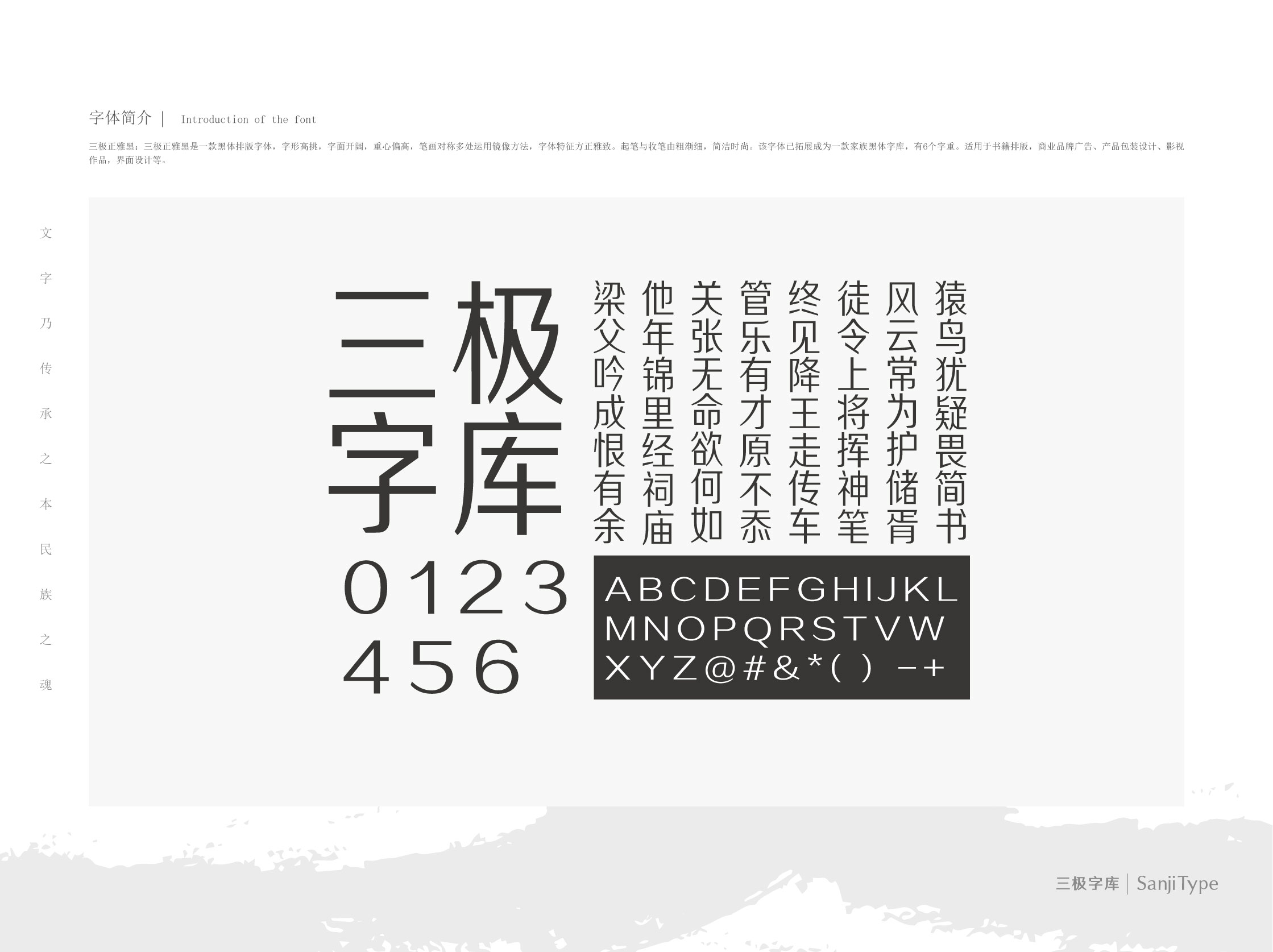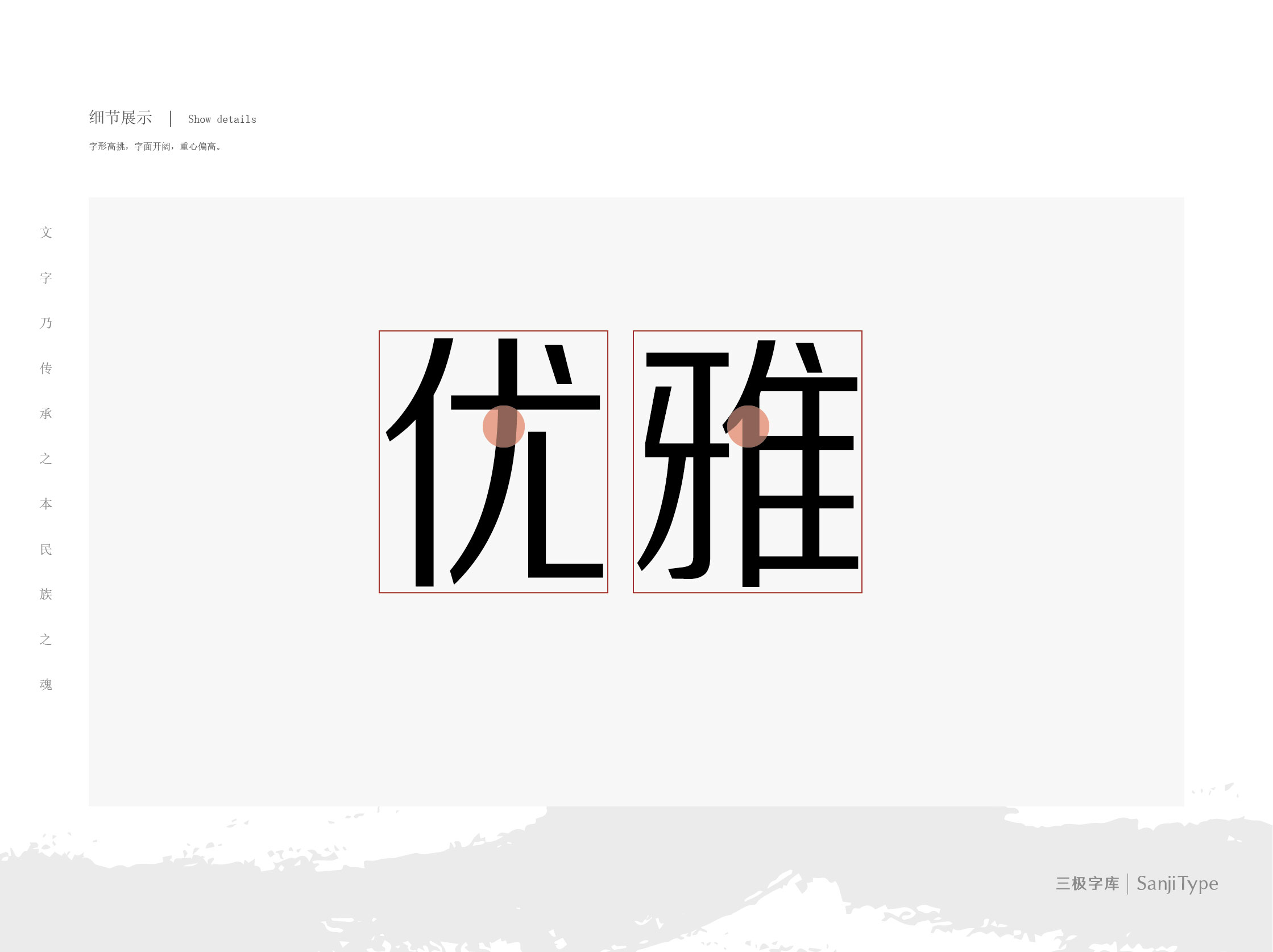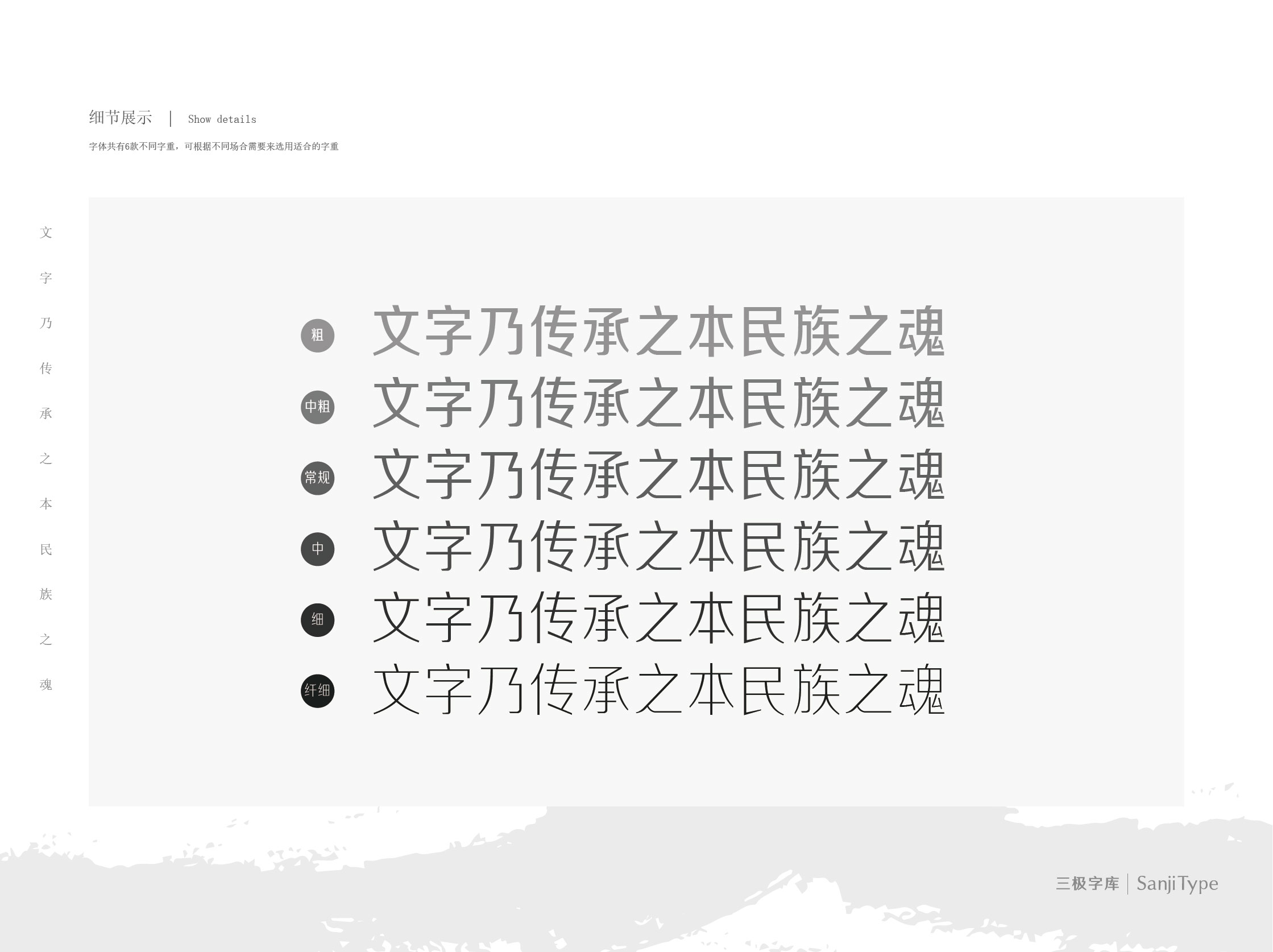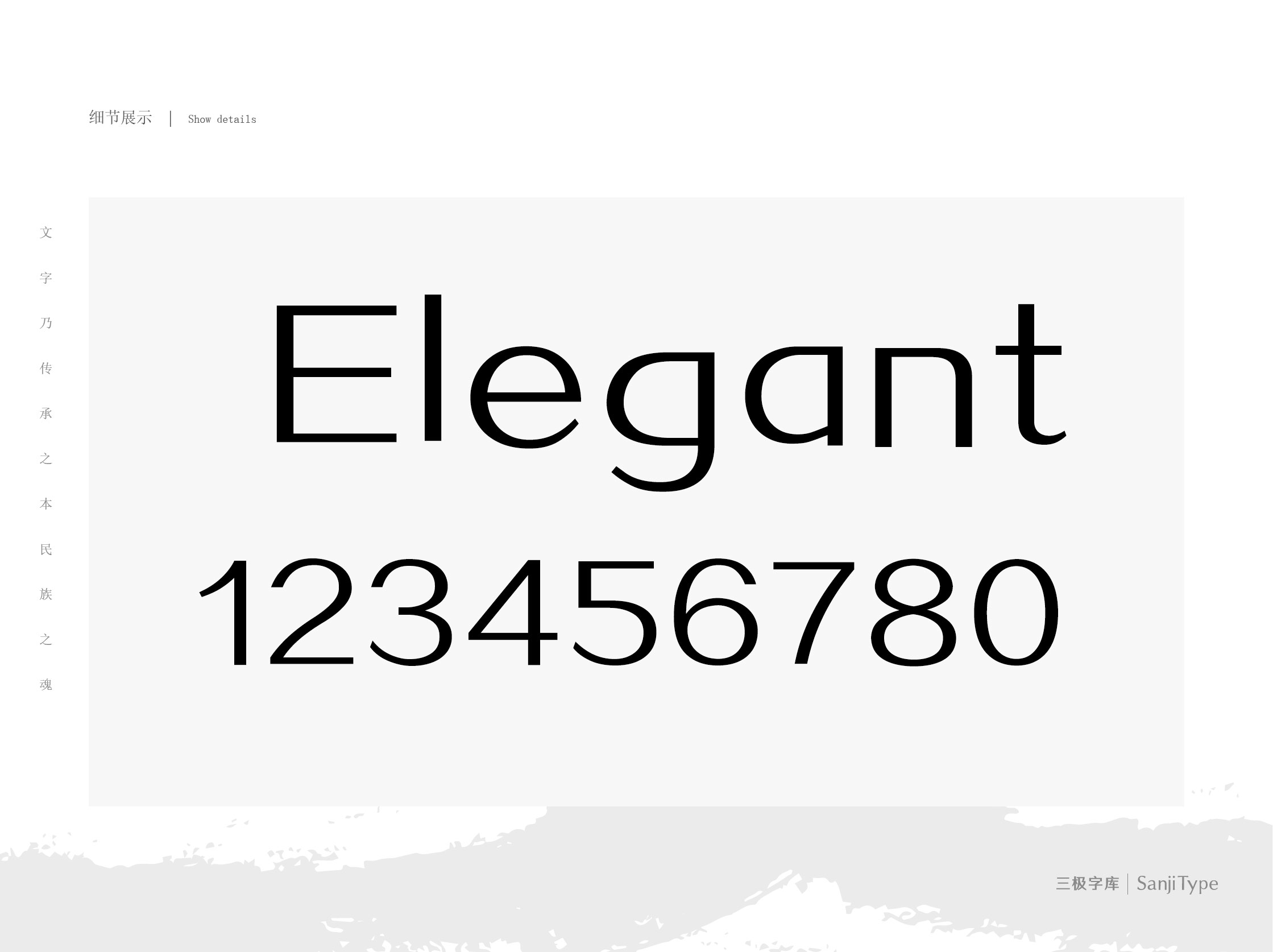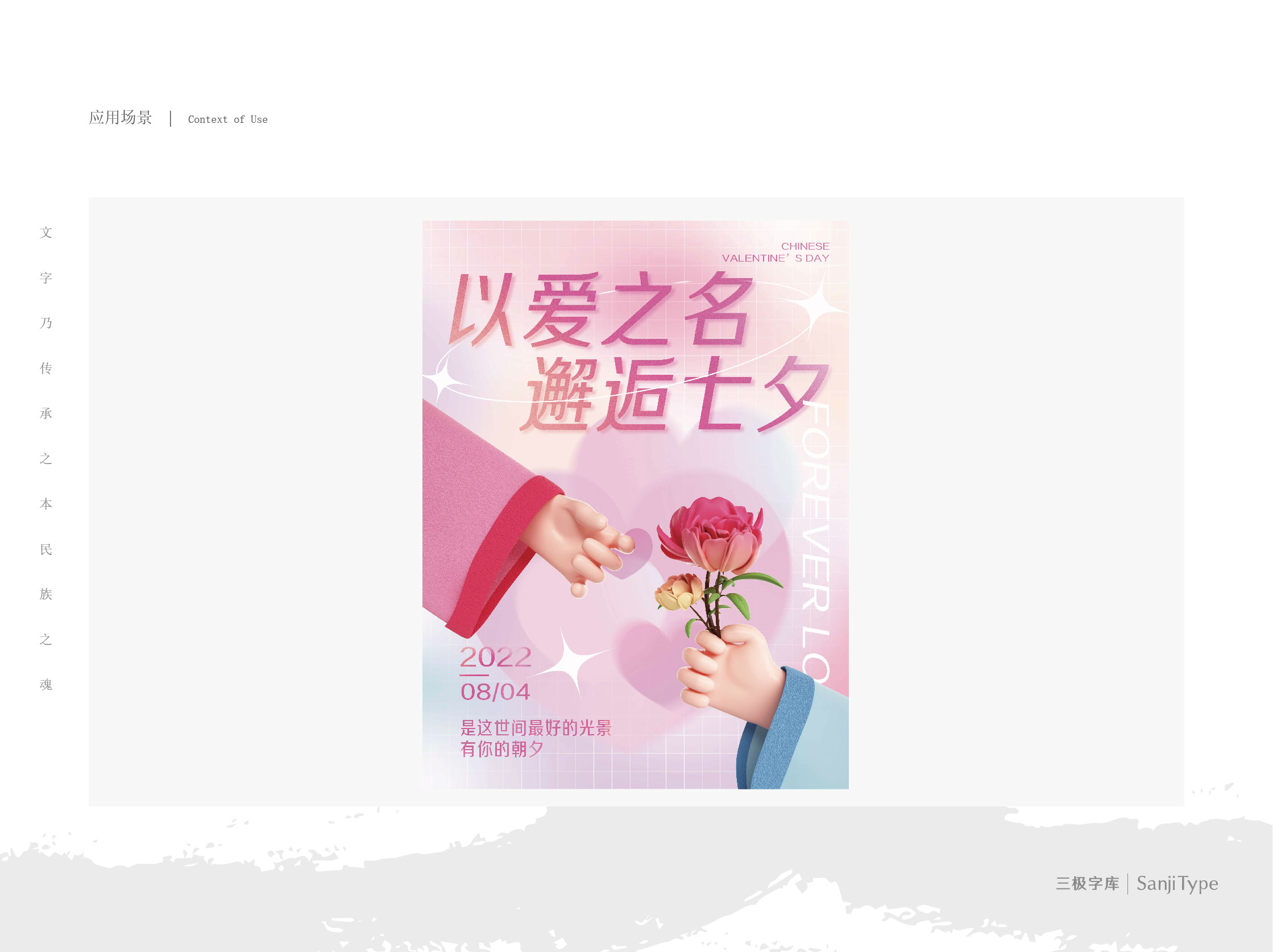
三极正雅黑家族
三极正雅黑 细
三极正雅黑 中
三极正雅黑
三极正雅黑 中粗
三极正雅黑 粗
三极正雅黑 纤细
黑体
三极正雅黑是一款创新的黑体,字形高挑,字面开阔,重心偏高,多处运用镜像方法使得笔画对称,起笔与收笔由粗渐细,简洁时尚。视觉上整体方正雅致、端庄简约。该字体已拓展为一款有六个字重的家族黑体字库,适用于书籍排版,商业品牌广告、产品包装设计、影视作品,界面设计等。